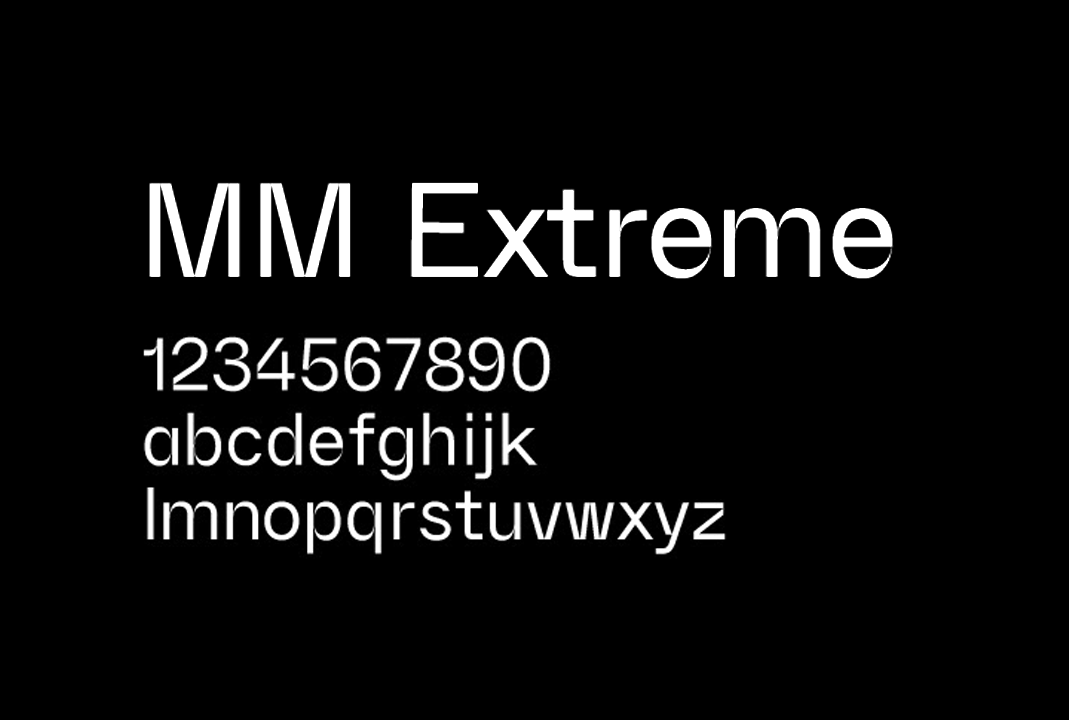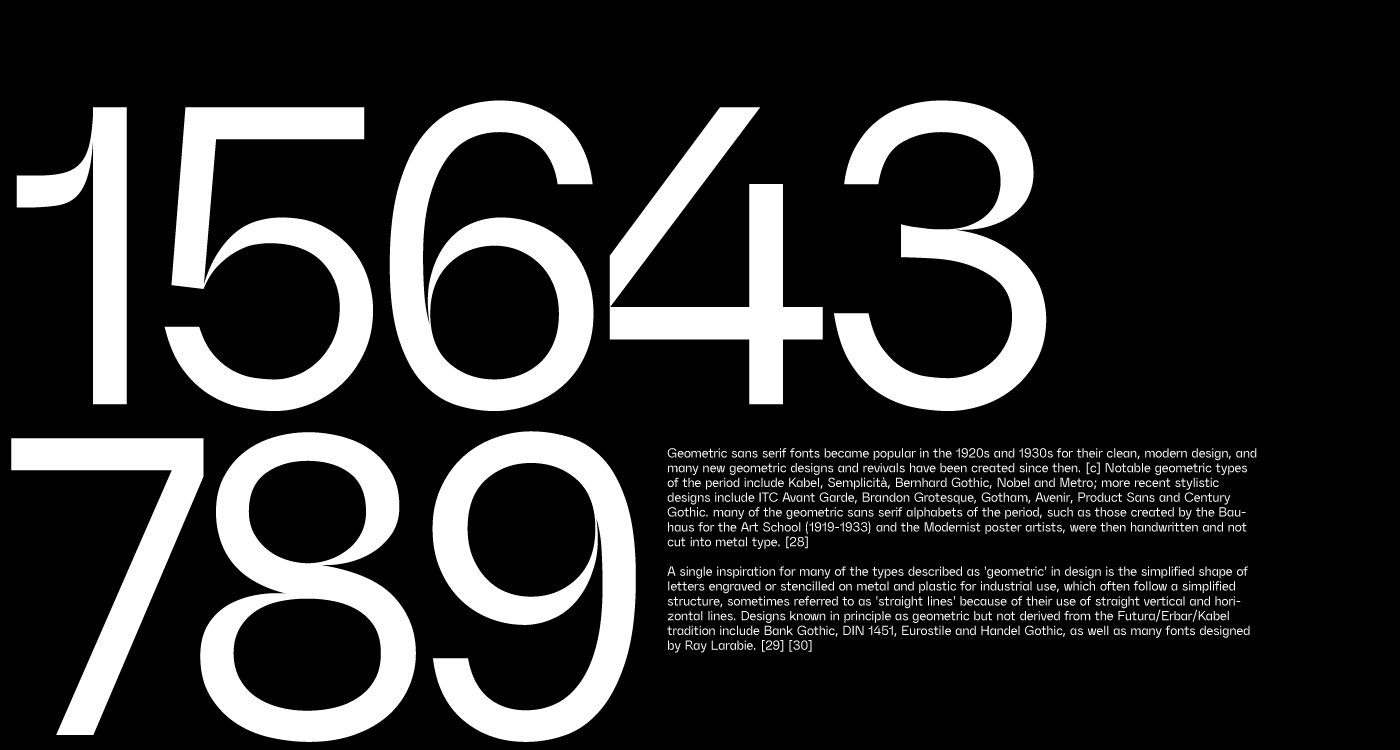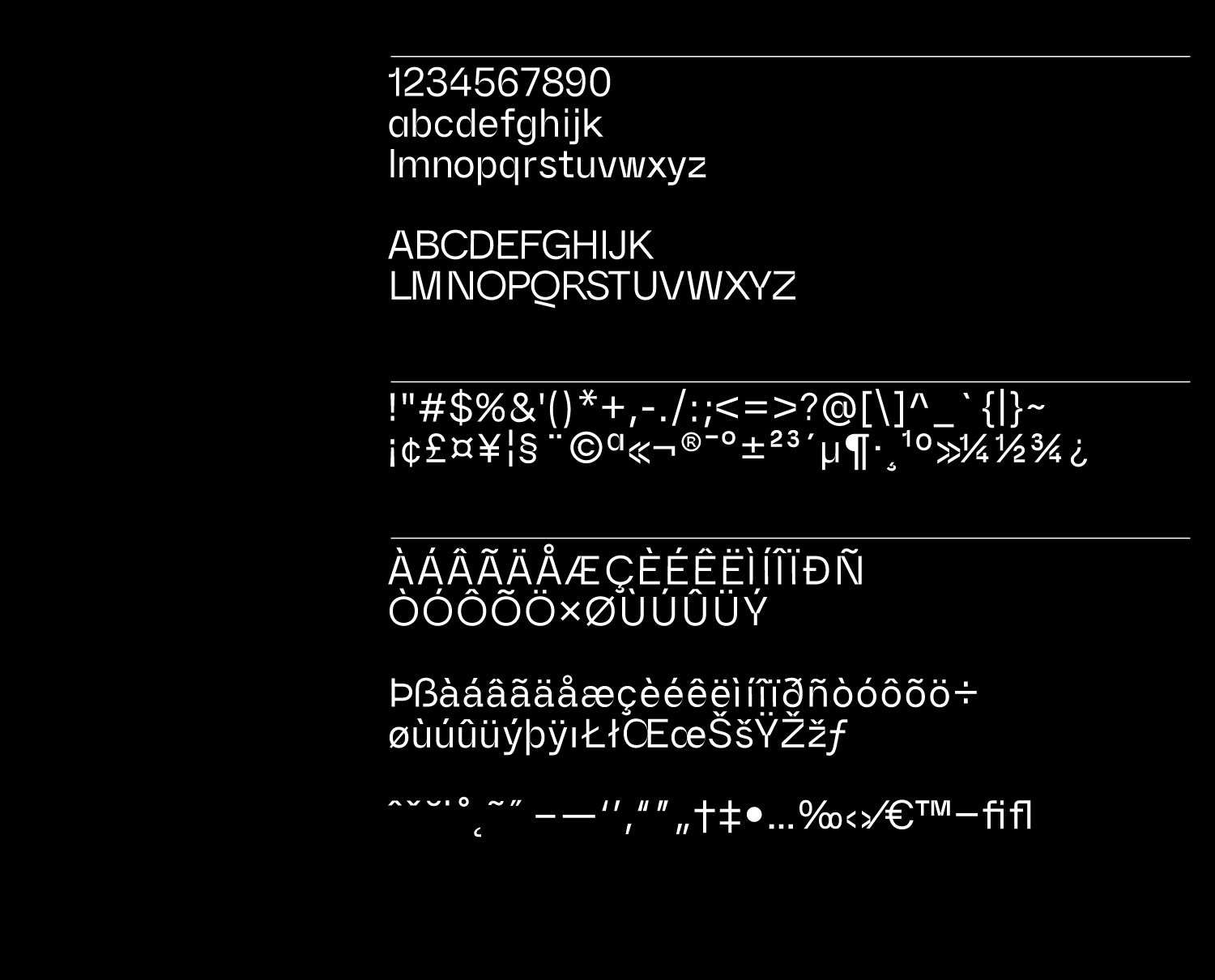
MM Extreme是由站酷网友(站酷ID:猛奇丨OneTwoOne)发布的一款可免费商用的英文字库,该字体是一款现代无衬线字体,采用扁平的形式和笔画分离的处理方式,大段文字的编排效果良好。提供 TTF、OTF 两种格式,并声明不论是个人还是企业都可以全媒体免费商用。
字体名称:MM Extreme
字符集标准:Adobe Latin 1
字符集数量:229(个)